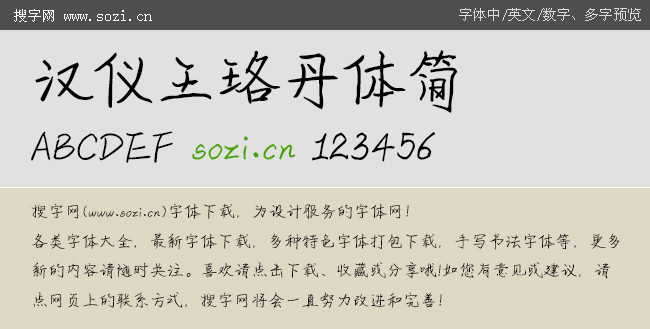
漢儀王珞丹體簡(jiǎn)
搜字網(wǎng)給大家提供一款漢儀王珞丹體簡(jiǎn)中文字體下載,本字體是一款由漢儀字庫(kù)根據(jù)人氣明星王洛丹的字體打造,給人字如其人的娟秀體驗(yàn),字體優(yōu)雅大方,看上去非常的舒心。喜歡的朋友就下載吧。
- 風(fēng)格類(lèi)別: 手寫(xiě)書(shū)法體